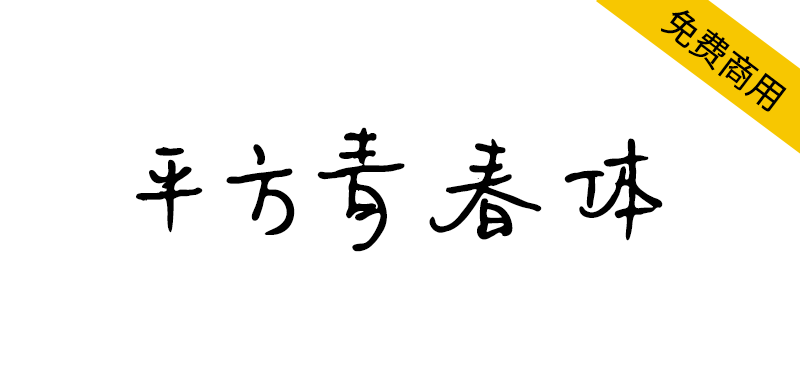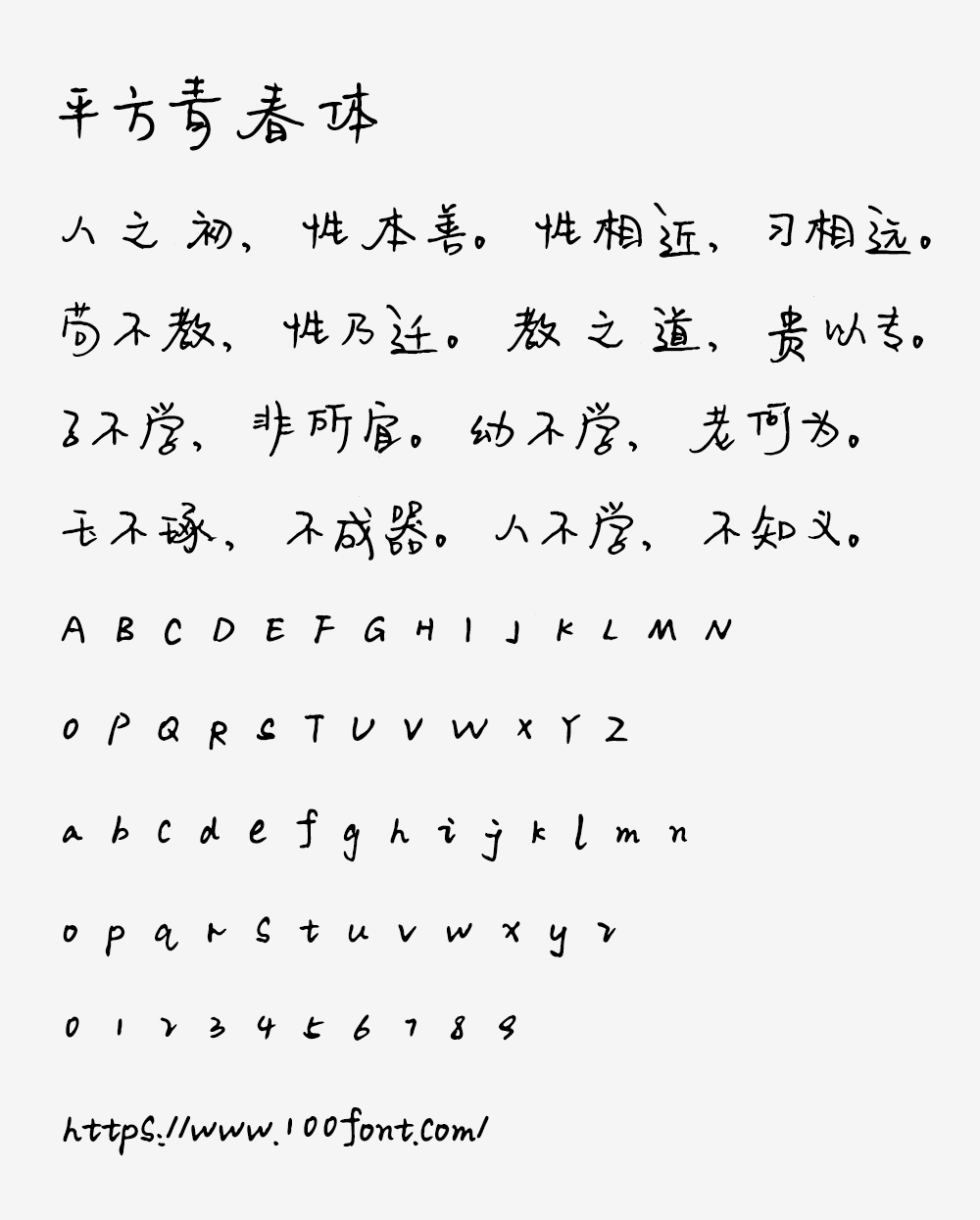
【平方青春体】一款充满文艺气息的手写风格字体
你是否在寻找一款既有文艺气质又百搭的手写字体?平方青春体,以流畅均匀的笔画、修长挺拔的字形和微微上扬的末端,悄然散发清新优雅的气息。支持在线预览,免费商用无压力,广告、自媒体、电商都能用。但不可修改或用于商标嵌入。点击体验,让设计多一份温柔诗意。
【平方青春体】一款充满文艺气息的手写风格字体
平方青春体是一款充满文艺气息的手写字体,线条流畅均匀,笔画末端微微上扬,字形修长挺拔,清新脱俗,散发着优雅的气质,适合用于各类文艺范场景。